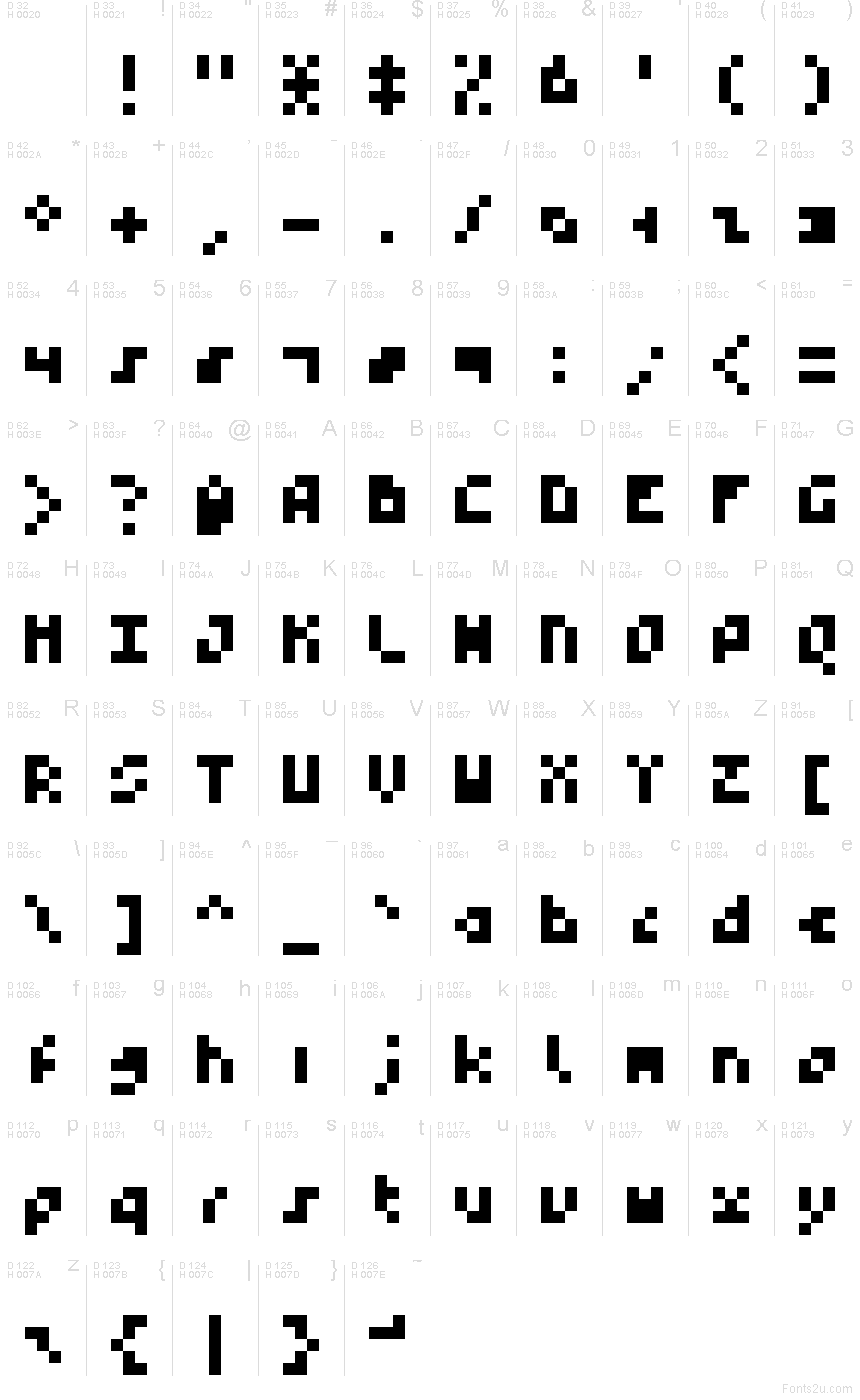
Pixlite de llosio es una tipografía bitmap de píxeles gratuita con el estilo directo y energético de los juegos de antaño. Sus letras están formadas por bloques cuadrados y ángulos rectos afilados, lo que le confiere un ritmo compacto y encajado en una rejilla que se siente más arcade que un simple ejercicio de nostalgia retro.
Es ideal para logotipos de juegos, pantallas de bienvenida de aplicaciones, títulos de pósteres, portadas de fanzines y etiquetas de interfaz cortas donde ese ritmo de bloques marque el tono. Al ser una fuente gratuita, también funciona muy bien para tarjetas de título, gráficos de pegatinas y encabezados breves que se benefician de su carácter de baja resolución y bordes definidos.
Auténtica tipografía de píxeles 3x5 con un principio de diseño único y estético.